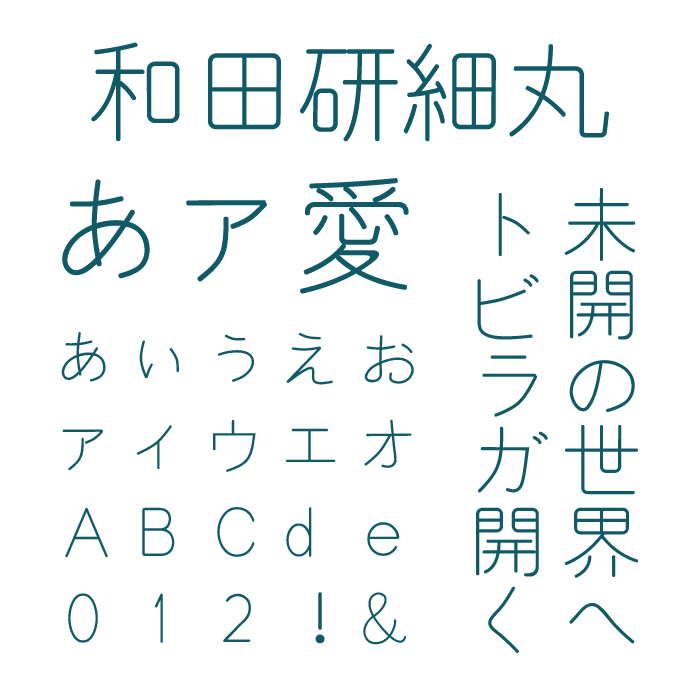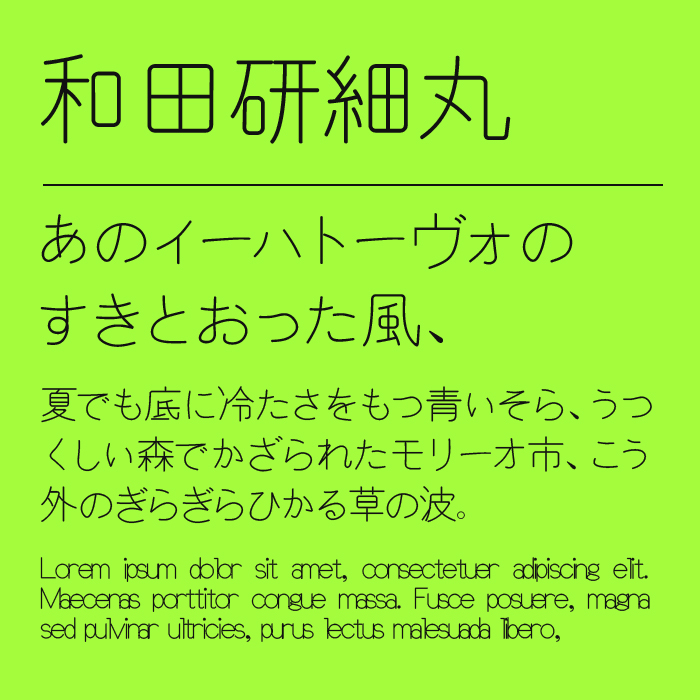
和田研細丸ゴシックフォントは、繊細で軽やかな線が特徴的な、やさしい雰囲気をもつ丸ゴシック系のフォントです。
極細の線で描かれた文字は、余白をたっぷり取りつつも、読みやすさが保たれており、読んでいてもストレスを感じられない視認性に優れています。ひらがな・カタカナともに端正で整っており、スマートな印象があります。
丸ゴシックの中でも、シンプルながら少し知的で上品なムードを漂わせており、詩的な文章や文学的なテキストと相性が良いです。ミニマルなレイアウトやナチュラル系のWeb・紙面デザインにもマッチするフォントです。